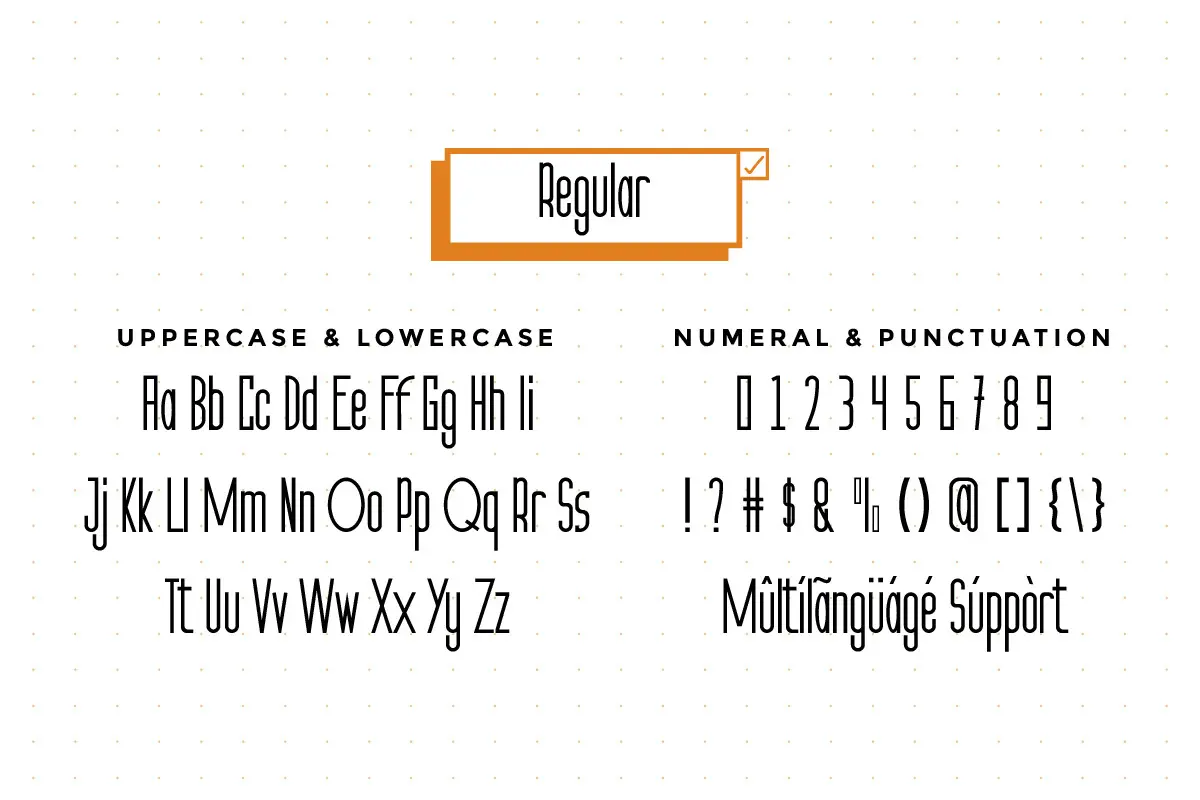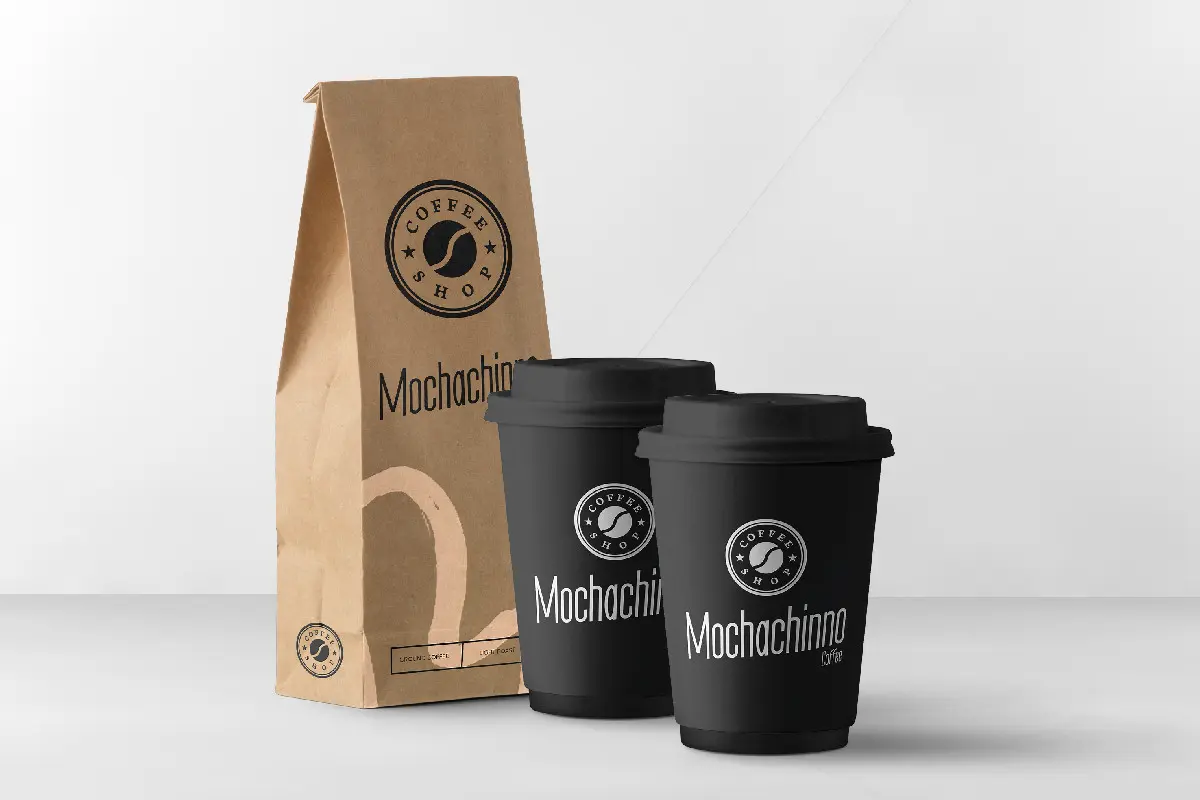
فونت مدرن و خلاقانه رایگان
فونت The Orange یک فونت سن سریف مدرن با استایل خلاقانه است که الهام گرفته از فضای کریپتوکارنسی و صنعت تکنولوژی طراحی شده. این فونت با خطوط ساده، خوانا و جذاب، انتخابی عالی برای پروژههای مدرن و آیندهنگر است.
- سبک: Sans Serif – فونت مدرن و مینیمال
- طراحی: خلاقانه، الهامگرفته از دنیای تکنولوژی و کریپتو
- انتخابی عالی برای پروژههای مدرن و تبلیغاتی
🎯 موارد استفاده:
- طراحی بستهبندی محصولات مدرن
- برندینگ و هویت بصری شرکتها و استارتاپها
- تیترها و سرتیترهای تبلیغاتی
- بیلبوردها و پوسترهای شهری
- پروژههای دیجیتال و وبسایتهای تکنولوژی